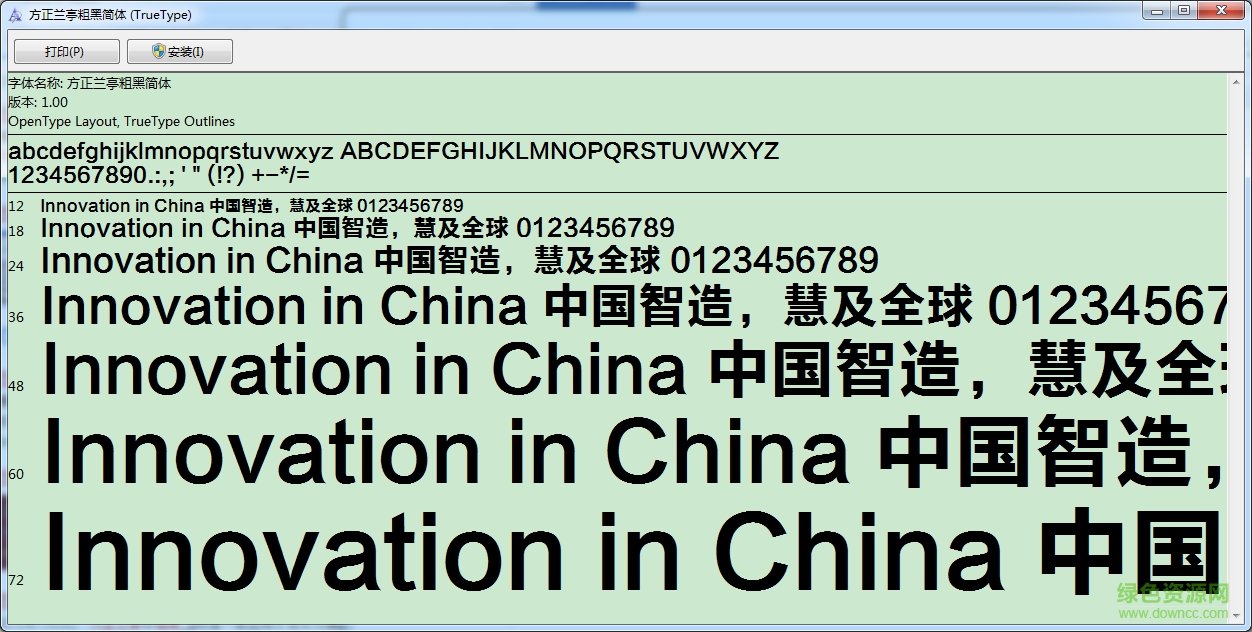
軟件介紹 軟件標簽: gbk10 方正字體 字體 fzltthk gbk1 0字體是一款非常時尚的字體哦,這款字體字形漂亮并且是方正字體中的其中一款哦,方正蘭亭粗黑哦,有需要的就來綠色資源網(wǎng)下載吧!fzltthk gbk1 0字體安裝方式方法一:控制面板/字體/文件/安裝新字體;方法二:直接將字體復(fù)制到C:\WINDOWS\Fonts。方法三:針對win7系統(tǒng),用戶只需選中字體右鍵安裝即可。注意事項本站所有字體資源僅供個人學(xué)習(xí)與參考,如需商業(yè)使用請到相關(guān)官網(wǎng)授權(quán)。 軟件截圖 上一張下一張(1 / 1) 安裝詳細截圖 猜你喜歡 ttf字體 ttf字體 中文字體ttf下載大全收錄了所有的ttf格式字體合集,這里的ttf字體資源豐富,種類齊全,包含了方正字體、漢儀字體、文鼎字體、華康字體等等,并且都可以免費下載使用,更多字體資源盡在ttf字體包下載專區(qū)! 查看更多>> nansongshuju字體 2.44M/中文/7.6/常規(guī)下載 禪意雪松體字體 2.44M/中文/0.2/免費版下載 指尖花涼體ttf 1.72M/中文/2.1/下載 宋體gb2312字體 2.44M/中文/2.5/下載 adobe premiere中文字體包 607.54M/中文/0.8/免費版下載 lixukexingshu regular 10.74M/中文/5.5/下載 其他版本下載 標題 大小 更新日期 下載 下載地址 電腦版 fzltthk gbk1 0 點擊報錯 軟件無法下載或下載后無法使用,請點擊報錯,謝謝! 關(guān)閉報錯反饋 請描述您所遇到的錯誤,我們將盡快予以修正,謝謝! *必填項,請輸入內(nèi)容 本類最新 dreamweaver字體庫 首爾南山體字體 v1.06 官方版 潮字社風(fēng)云簡ttf 潮字社凌渡鯤鵬簡體字體 潮字社曾玉波手書簡字體 微博慧心字體 相關(guān)文章 Photoshop字體安裝使用方法和技巧 如何解決“無法新增字體”問題 Win 7系統(tǒng)安裝字體方法 網(wǎng)頁字體大小設(shè)置方法 怎么改網(wǎng)頁字體大小 在Linux系統(tǒng)中安裝字體的幾種方法 windows7字體顯示問題:打開某些程序的時候顯示的是亂碼 用戶評論 熱門評論 最新評論 第 1 樓 天津客人 發(fā)表于: 2021/05/21 18:22:39 輸入中英文效果都很好 支持(2) 蓋樓(回復(fù)) 發(fā)表評論 查看所有評論(1) 昵稱: 請不要評論無意義或臟話,我們所有評論會有人工審核. 字數(shù): 0/500 (您的評論需要經(jīng)過審核才能顯示)